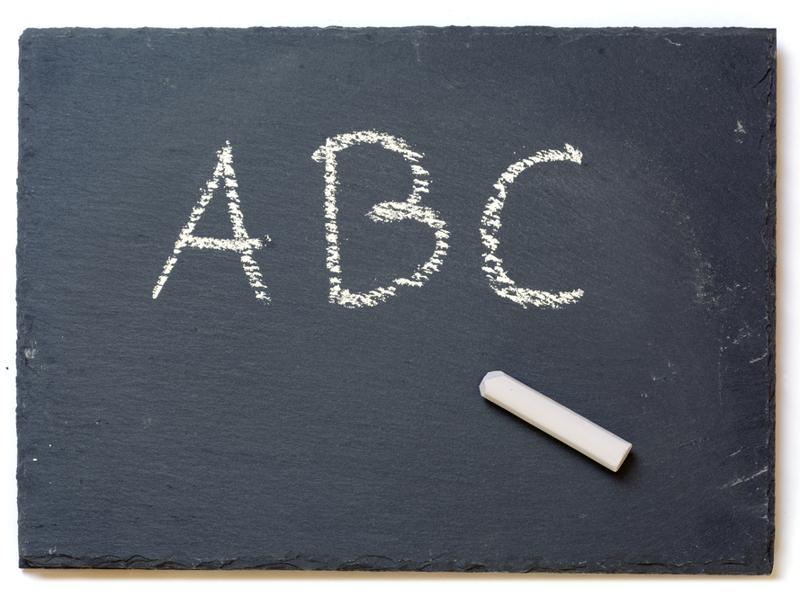
Ретро-эффект мела на доске в Photoshop. Кисть для фотошопа мелом на доске
В этом уроке мы создадим ретро-работу в Adobe Photoshop. Мы совместим несколько различных элементов, чтобы создать желаемую композицию. Вы узнаете как при помощи фотографии, графики, шрифтов и эффектов создать такой постер:
Результат
- Шрифт American Captain
- Шрифт Chalk Font
Шаг 1
Откройте Photoshop и создайте новый файл размером 1920×1280 (Ctrl + N). Откройте изображение доски и выделите всё, нажав Ctrl + A. Копируйте выделенное (Ctrl + C) и вернитесь в наш документ.
Нажмите Ctrl + V, чтобы вставить скопированное в наш документ. Вы можете разместить изображение как вам больше нравится и, при желании, трансформировать его, нажав Ctrl + T (режим свободного трансформирования).
Шаг 2
Откройте изображение женщины. Инструментом Pen/Перо (P) создайте контур вокруг женщины. После этого нажмите Ctrl + Enter, чтобы преобразовать контур в выделение.
Нажмите Ctrl + C, чтобы копировать выделение, затем вернитесь в наш документ и нажмите Ctrl + V, чтобы вставить скопированное. Масштабируйте изображение в режиме свободной трансформации (Ctrl + T) и разместите женщину как показано ниже.
Шаг 3
Так как иллюстрация будет в стиле ретро, нам нужно обесцветить изображение женщины. Создайте новый корректирующий слой: Layer > New Adjustment Layer > Hue/Saturation / Слой>Новый корректирующий слой>Цветовой тон/Насыщенность. Укажите корректирующему слою обтравочную маску по контуру силуэта женщины. Для этого, удерживая Alt, кликните между слоем с женщиной и корректирующим слоем. Настройте параметры слоя как показано ниже.
Шаг 4
Цвета на изображении с женщиной получились слишком блеклыми. Для этого нам нужен еще один корректирующий слой: Layer > New Adjustment Layer > Curves/Слой>Корректирующий слой>Кривые. Также укажите этому слою маску по контуру слоя с женщиной. Настройте кривые как показано ниже.
Шаг 5
Чтобы добавить реализма, давайте добавим теней.
Создайте новый слой (Ctrl + Shift + Alt + N) и поместите его между слоями с женщиной и доской. Возьмите стандартную круглую растушеванную кисть и снизьте ее Оpacity/Непрозрачность на 50%.
Рисуйте черным цветом в местах, показанных на картинке ниже, чтобы создать эффект тени.
Шаг 6
Теперь нарисуем рамку. Для начала создайте новый слой (Ctrl + Shift + Alt + N) и поместите его под слоем с тенью. Возьмите стандартную кисть-мел и нарисуйте рамку, как показано ниже. Чтобы линии были идеально прямыми, удерживайте Shift во время рисования. После этого снизьте Fill/Заливку слоя до 50%.
Шаг 7
Шаг 8
Введите слово (в нашем примере это “SCIENCE” размера в 275pt и белого цвета) и в режиме свободного трансформирования разместите его как показано ниже.![]()
Шаг 9
Добавим шрифту ретровости.
Кликните по нему правой кнопкой мыши и из выпавшего меню выберите “Blending Options/Параметры наложения”. Добавьте указанные ниже стили слоя.
Шаг 10
Добавим еще немного текста уже другим шрифтом — “Chalk Font”. Если у вас несколько строк текста, создавайте каждую строку в отдельном слое. Затем сгруппируйте все слои текста, нажав Ctrl + G.
Шаг 11
Так как эта надпись сделана мелом, она не может быть такой однородной и равномерно белой как мы видим. Поэтому нужно добавить элемент случайности.
Создайте слой-маску для группы с текстом мелом (Layer > Layer Mask > Reveal all/Слой>Маска слоя>Показать все). В маске рисуйте кистью-мелом черного цвета на 40% opacity/непрозрачности в некоторых местах поверх текста, чтобы частично его скрыть. Также снизьте opacity/непрозрачность группы до 70%.
Шаг 12
Добавим немного легкомысленной графики. Откройте изображение ракеты, копируйте ее и вставьте в наш документ.
В режиме свободной трансформации (Ctrl + T) разместите ракету как показано ниже.
Шаг 13
Кликните дважды по слою с ракетой, чтобы открыть окно стилей слоя. Укажите слою указанные ниже стили.
Шаг 14
Чтобы наше изображение выглядело еще более ретро, нам нужно добавить зернистость. Создайте новый слой из всех видимых слоев (Ctrl + Shift + Alt + E), затем выберите в меню Filter > Noise > Add Noise/Фильтр>Шум>Добавить шум и настройте фильтр как показано ниже.
Шаг 15
Осталось только добавить виньетку для завершенности вида. Создайте новый слой и залейте его белым цветом (Shift + F5).
В меню выберите Filter > Lens Correction/Фильтр>Коррекция дисторсии и перейдите в закладку Custom/Дополнительно. Настройте параметры как показано ниже и нажмите ok. Смените blending mode/Режим наложения слоя на Multiply/Умножение.
Этот урок научит вас, как использовать кисть и её настройки для создания текста с эффектом мела.
Материалы для урока:
Откройте изображение с доской в фотошоп и с помощью инструмента Рамка (Crop Tool) избавьтесь от углов с чёрным фоном.
The Chalker — Шрифт для надписей мелом
Грубый шрифт в один штрих с текстурой и ощущением мела на нем, так что вы можете получить ощущение «автоматического мела» в мгновенных движениях.
Truesketch
TrueSketch — забавный, практичный и универсальный шрифт, который можно использовать в различных цифровых проектах.
Ручной шрифт без засечек
Шрифт BrideChalk
BrideChalk вдохновлен множеством надписей на фоне мелом на свадьбе и приглашении на свадьбу мелом.